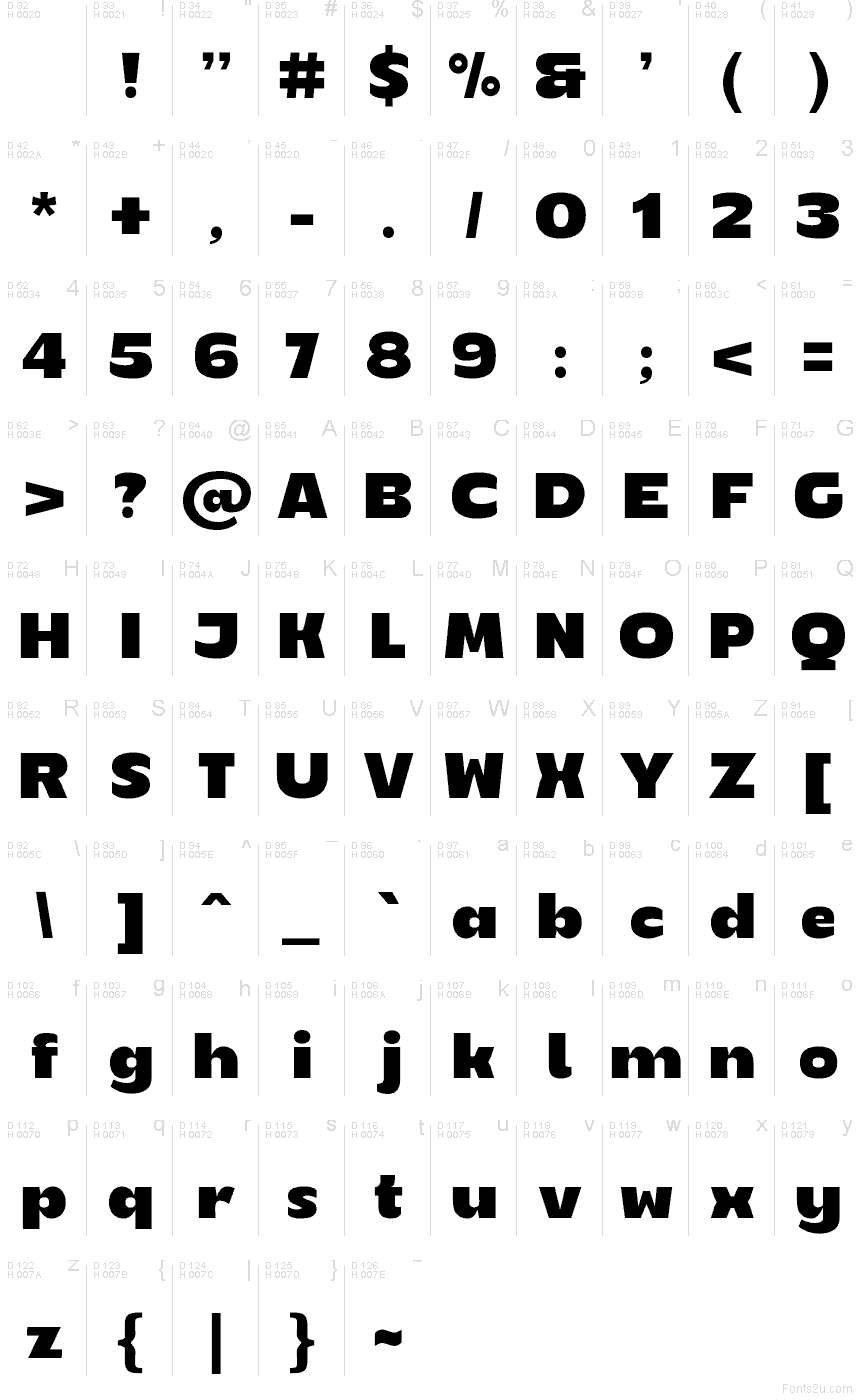
Písmo Mertune Light od Muhamada Fikry Nuralifa z Fikryal Studio vnáší do rodiny Mertune robustní a sebevědomý hlas, který zůstává čistý a skvěle čitelný. Tvary jsou široké a výrazné, s jemnými čtvercovými křivkami, takže nadpisy působí hlasitě, aniž by vypadaly přeplácaně nebo stísněně. Je to moderní bezplatné bezpatkové písmo stvořené pro odvážná sdělení, která přesto působí úhledně.
Mertune Light vynikne na plakátech, úvodních obrazovkách aplikací, obalech, náhledech videí na YouTube, akčních letácích, značkách a reklamách na sociálních sítích, kde potřebujete okamžitý efekt. Pro hlavní text ho zkombinujte s klidnějším humanistickým sans-serifem nebo neutrálním groteskem a při použití ve velkých velikostech mu dopřejte trochu více prostrkání – toto písmo zdarma potřebuje prostor k dýchání.